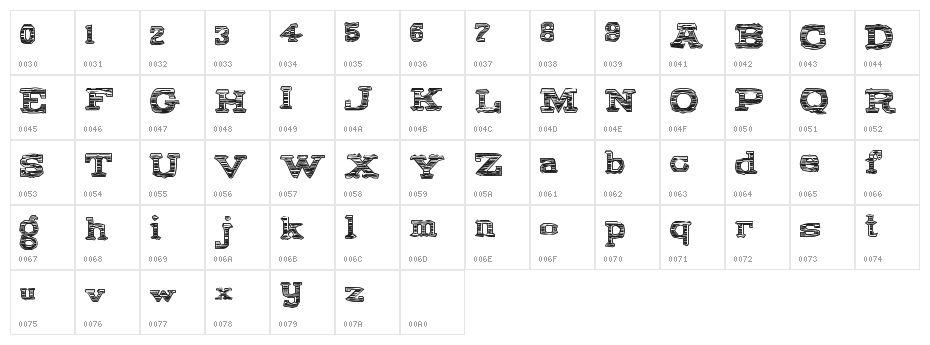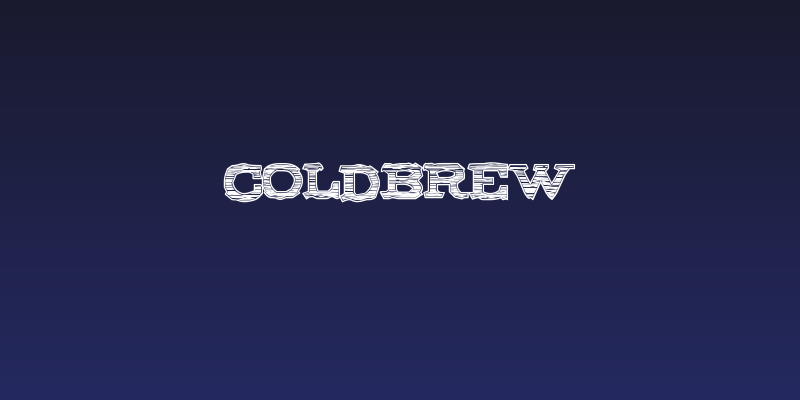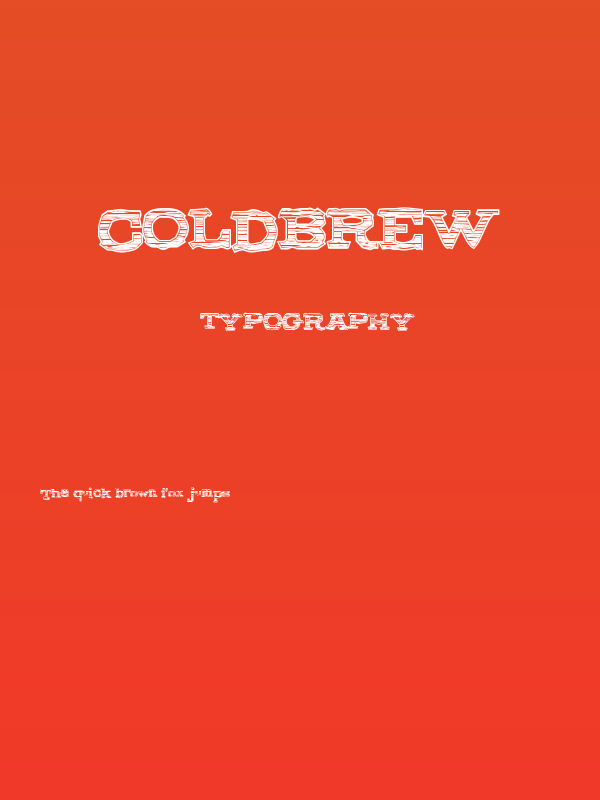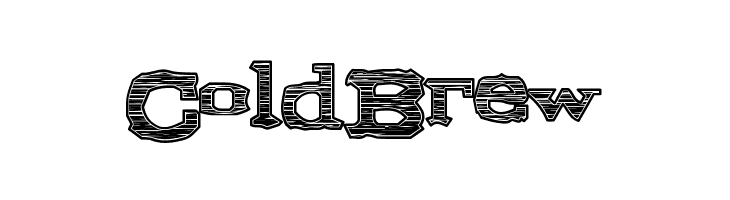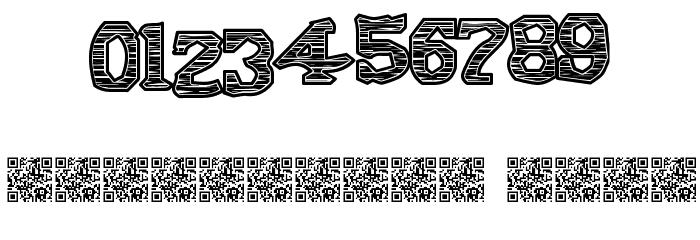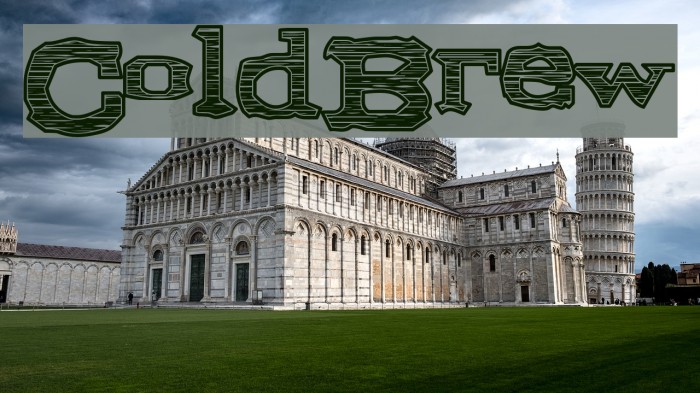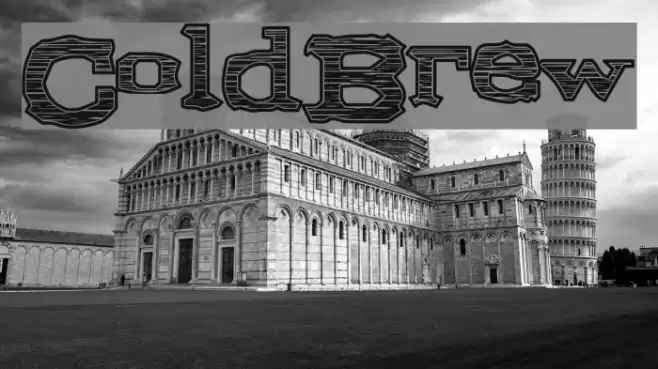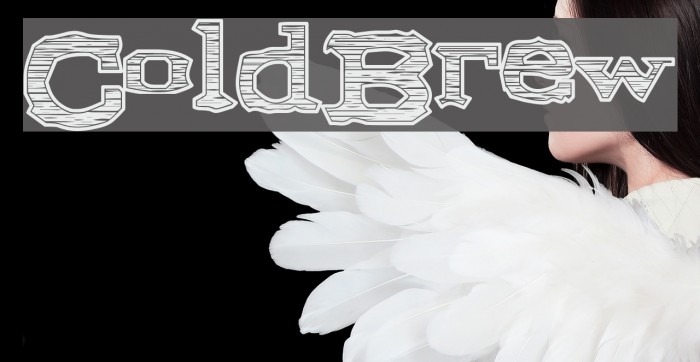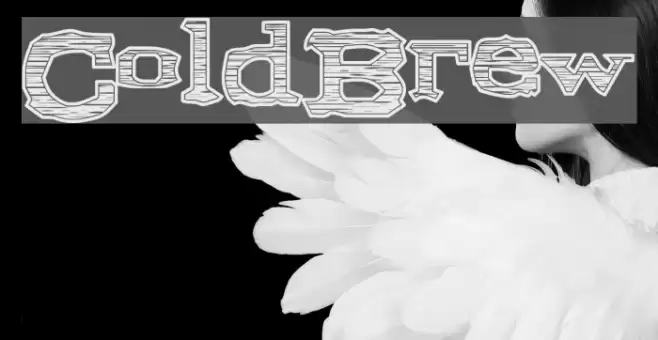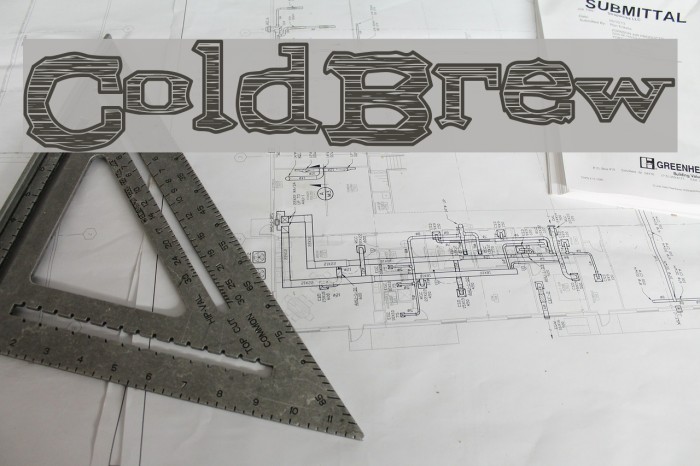
ColdBrew Font
| कंट्रास्ट | High |
| समग्र शैली | Modern, Industrial |
| उपयोग का मामला | Headlines, Logos, Posters |
| सुझाए गए प्रोजेक्ट | Ideal for posters, logos, branding, and any design that requires a striking, modern aesthetic. |